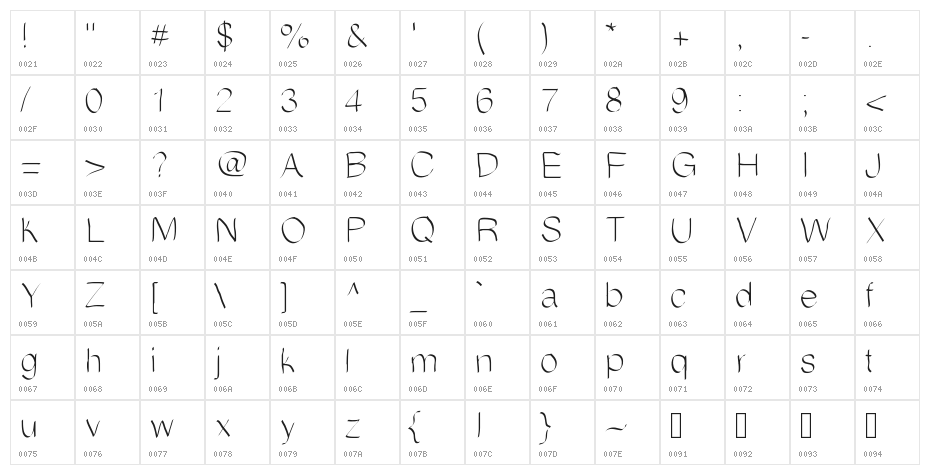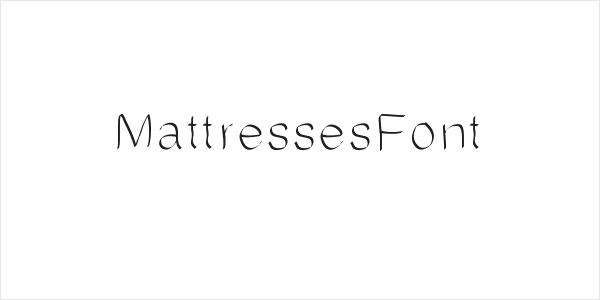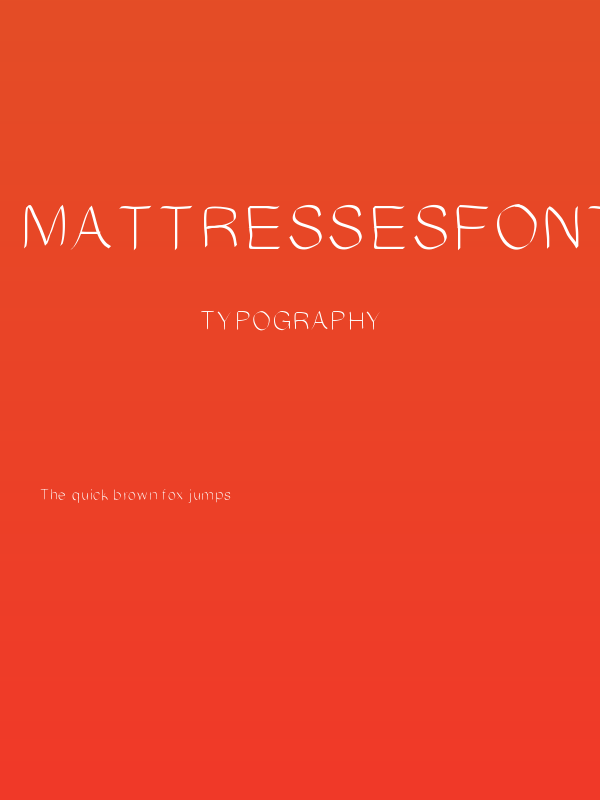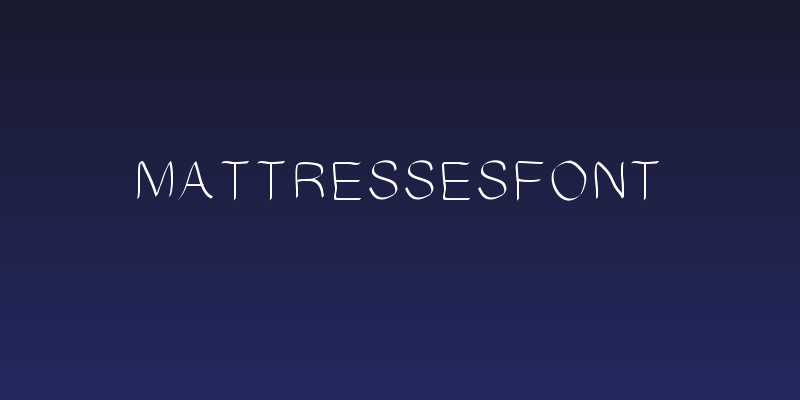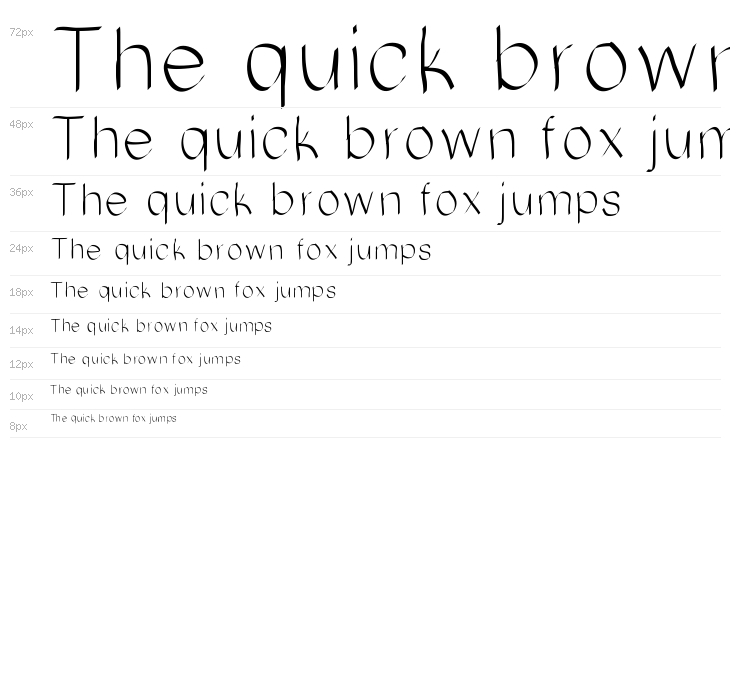
MattressesFont Font
MATTRESSESFONT 大文字
MATTRESSESFONT 小文字
MATTRESSESFONT その他の文字
| おすすめプロジェクト | Ideal for greeting cards, children's books, creative branding, and artistic posters. |